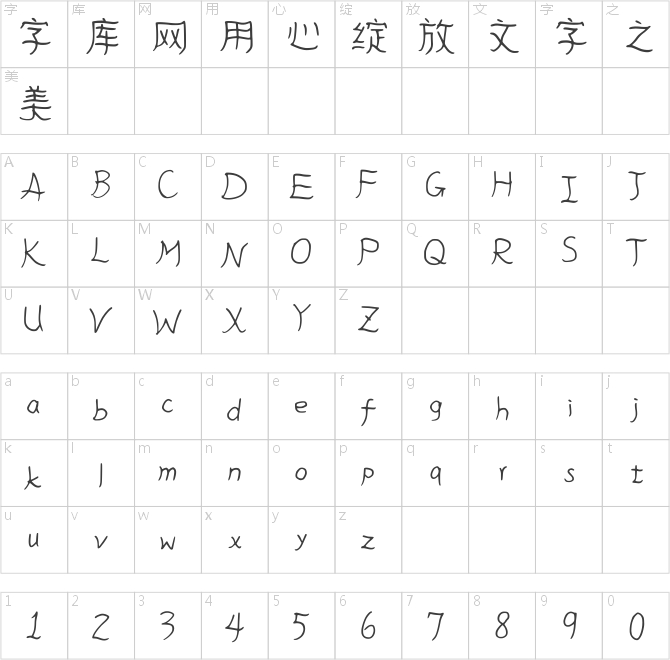
字体名称: 清松手写体7
“清松手写体7”作为游清松先生倾力打造的第七款免费可商用字体系列作品,延续了该系列一贯的人性化与自然书写特色。这款字体在2024年初次亮相,标志着清松手写体家族的又一次重大突破与迭代升级。
“清松手写体7”以独特的原子笔质感为基础,融入了更多现代审美趋势,字形结构更加丰富多样且不失和谐统一。设计师游清松深入研究汉字书写美学,通过细腻的笔画勾勒与微妙的转折变化,使得每一个字符都仿佛跃然纸上,充满了生命力和温度。